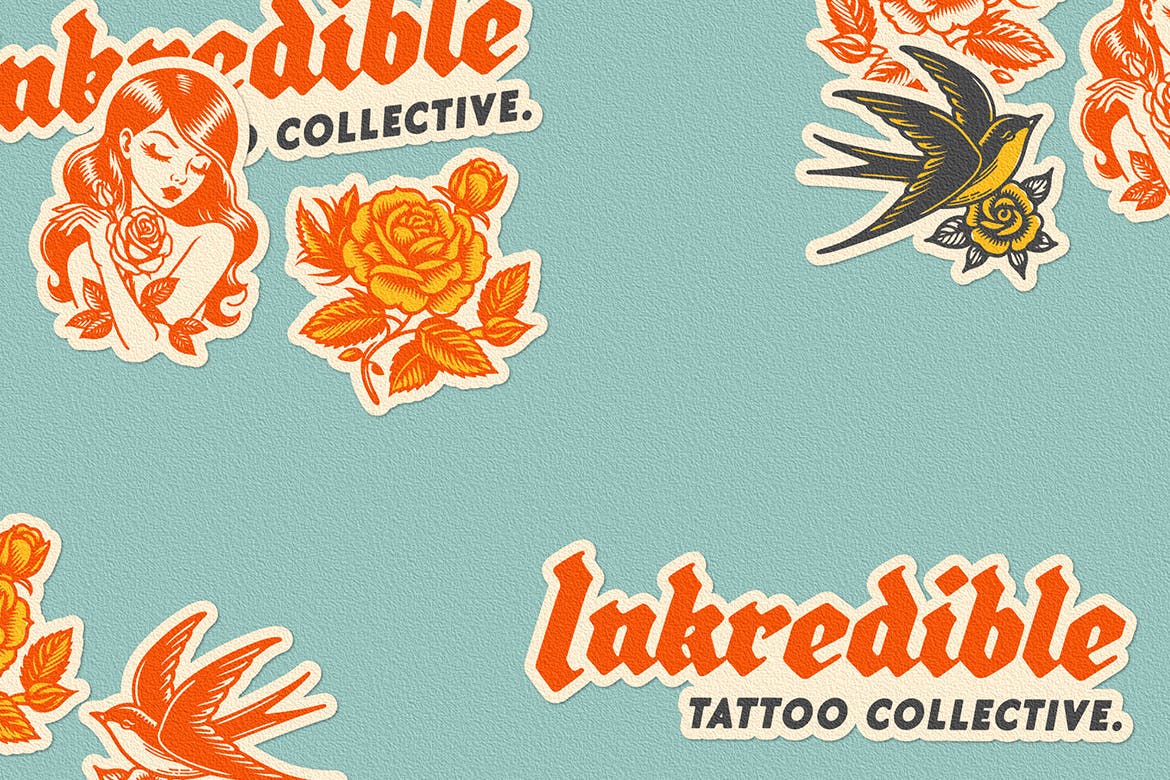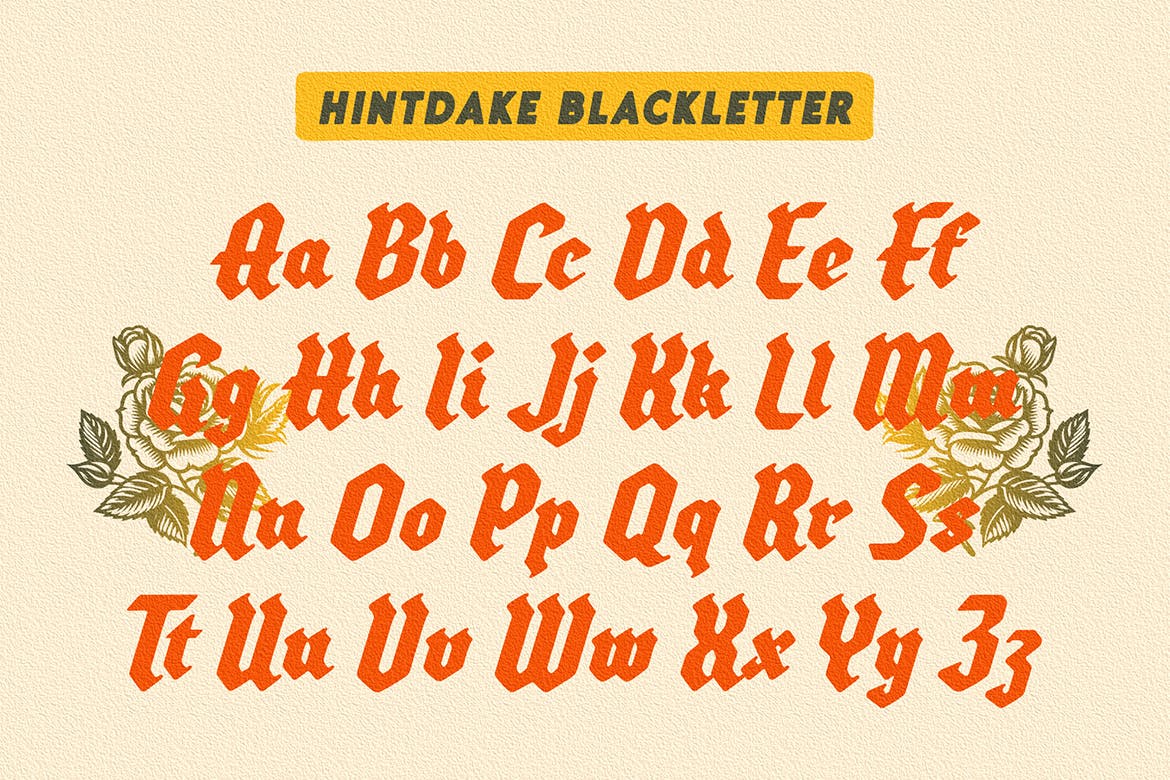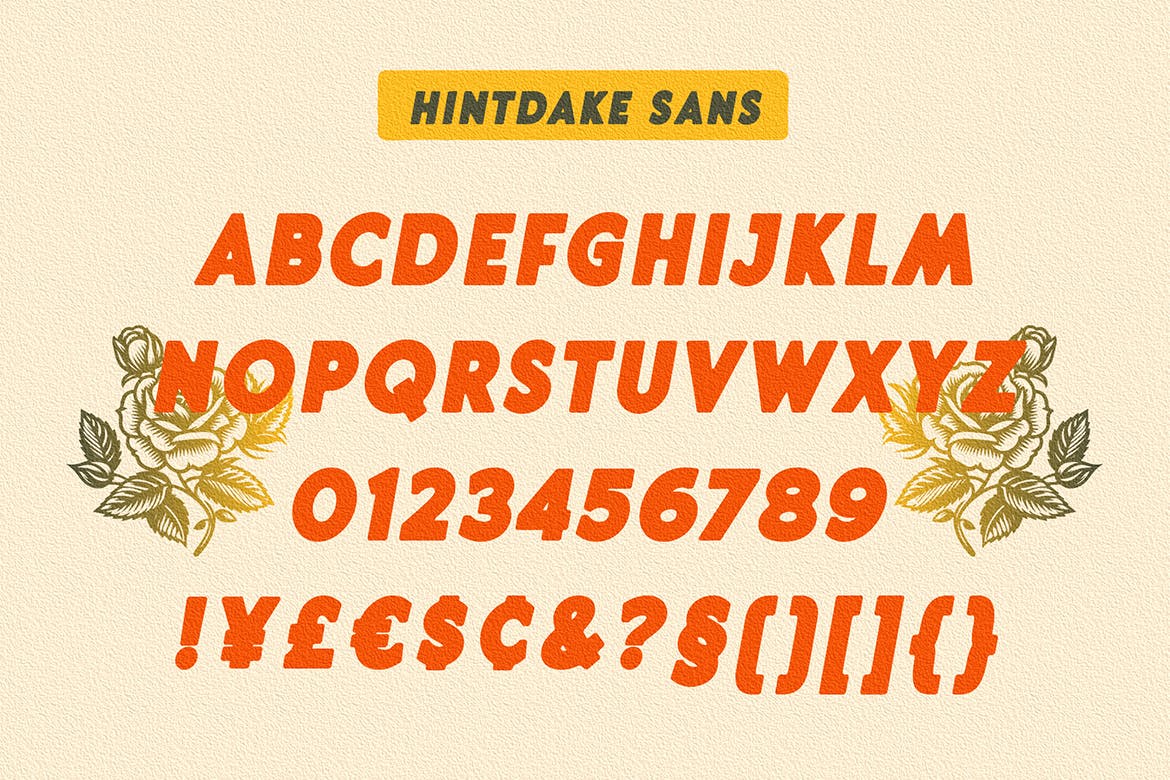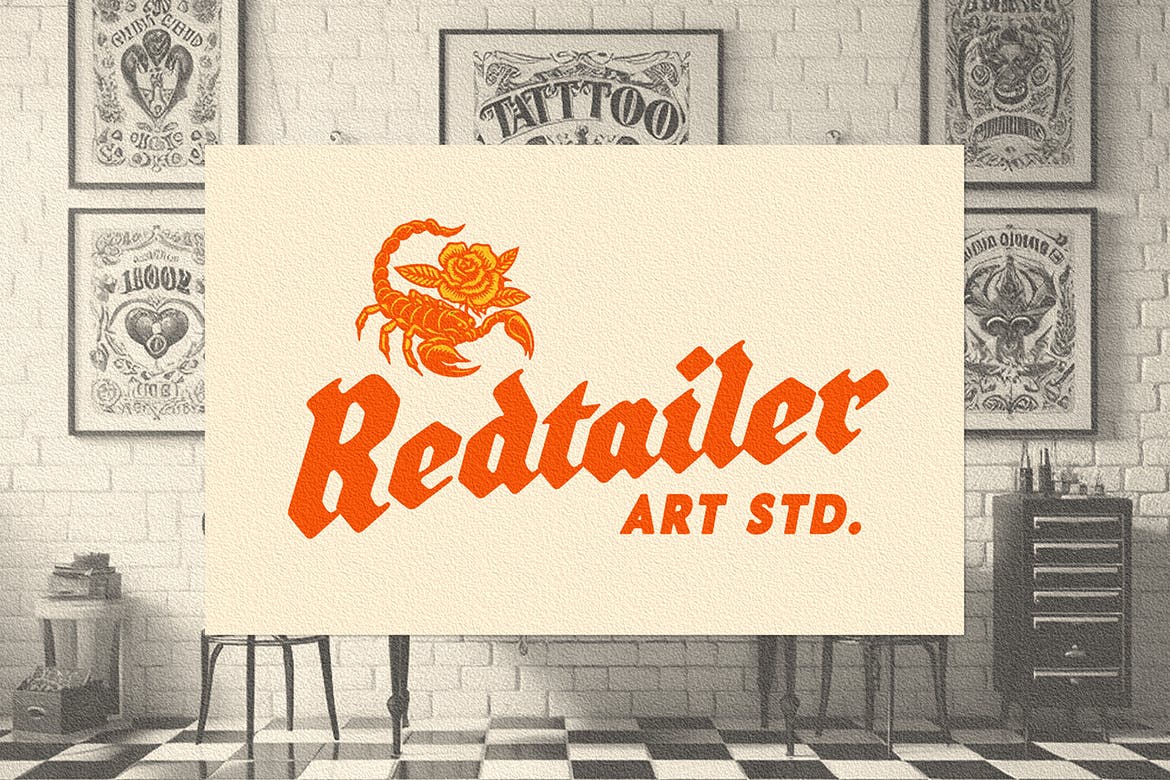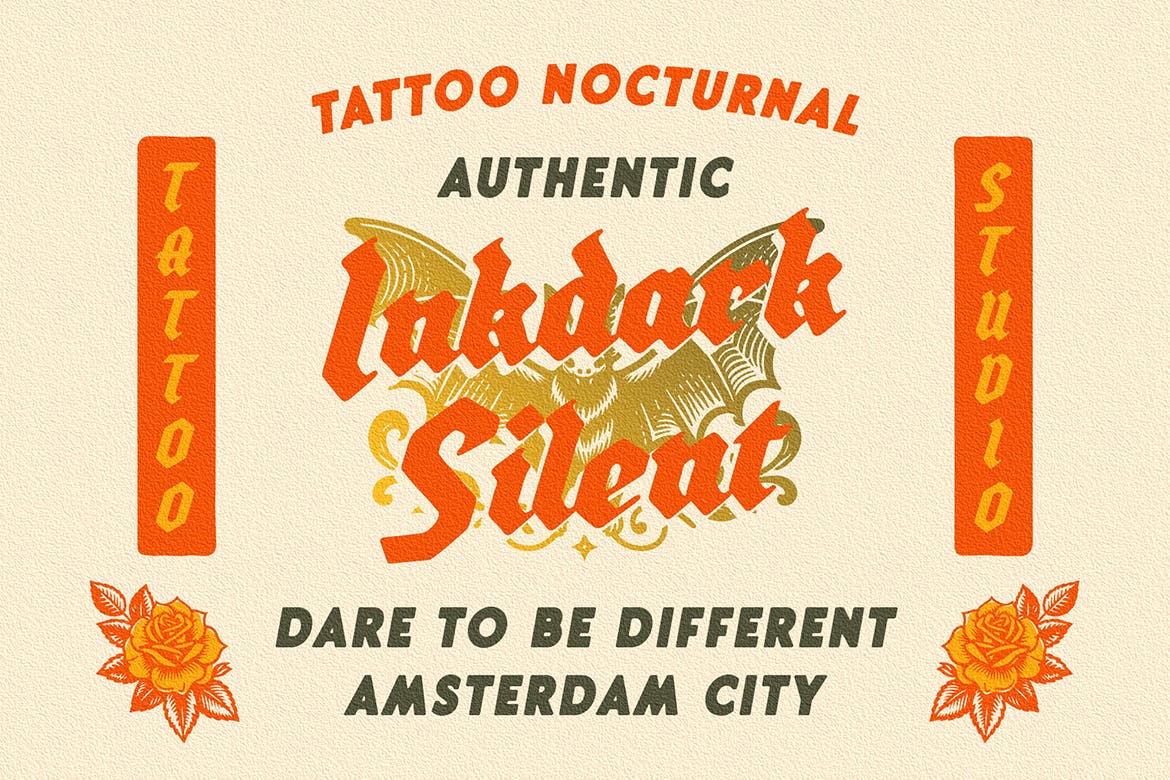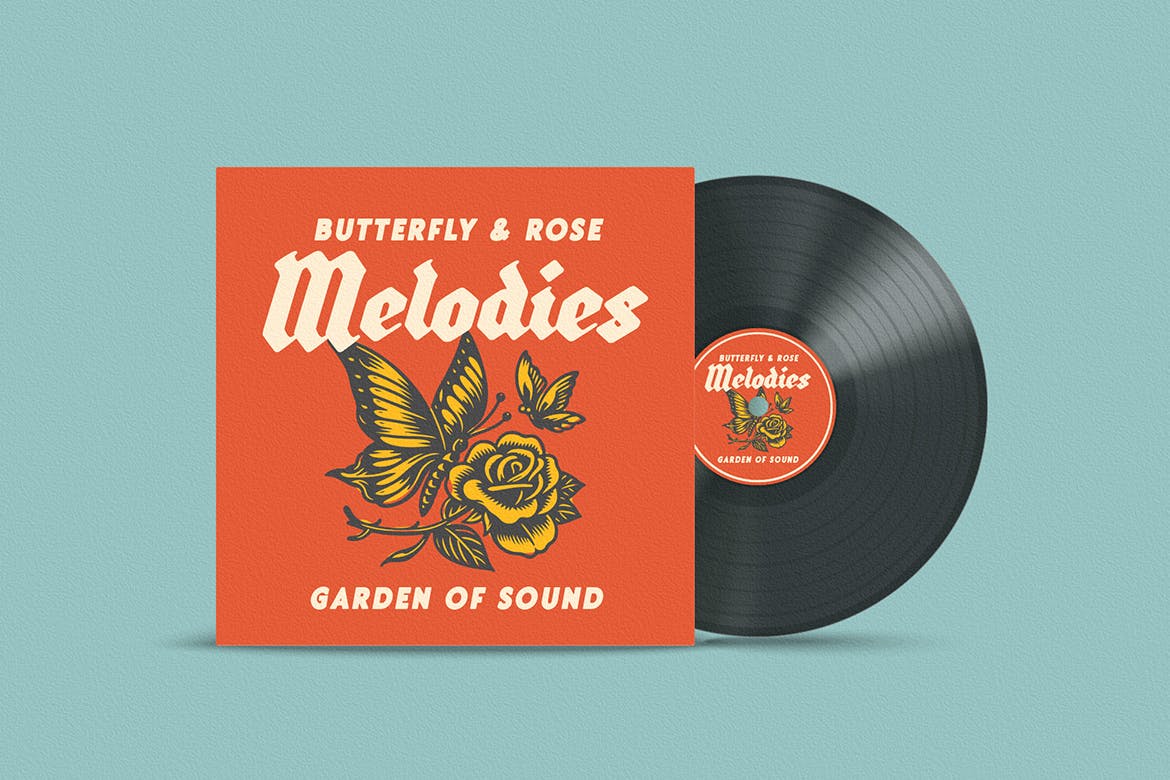
Hintdake Tattoo Blackletter Font
با فونت Hintdake، طراحی‌های خلاقانه و جذاب را تجربه کنید.
Hintdake تنها یک فونت نیست، بلکه کلید ورود شما به دنیای فونت‌های تتو است. این مجموعه شامل سه سبک (معمولی، خشن و مهر) می‌باشد. Hintdake سلاح مخفی شما برای لوگوها، برندینگ و طراحی‌های متمایز است. به دنیای فونت‌های بلک لتر وارد شوید و با این مجموعه استثنایی اثر خلاقانه خود را بگذارید.
ویژگی‌های فونت Hintdake :
• 8 فونت (بلک لتر، سنس سریف و دنگبت)
• 3 سبک تایپ‌فیس (معمولی، خشن و مهر)
• حروف بزرگ، کوچک، اعداد، نمادها، نشانه‌گذاری و لیگاتور در فونت بلک لتر
• حروف بزرگ، اعداد، نمادها و نشانه‌گذاری در فونت سنس سریف
• چند زبانه